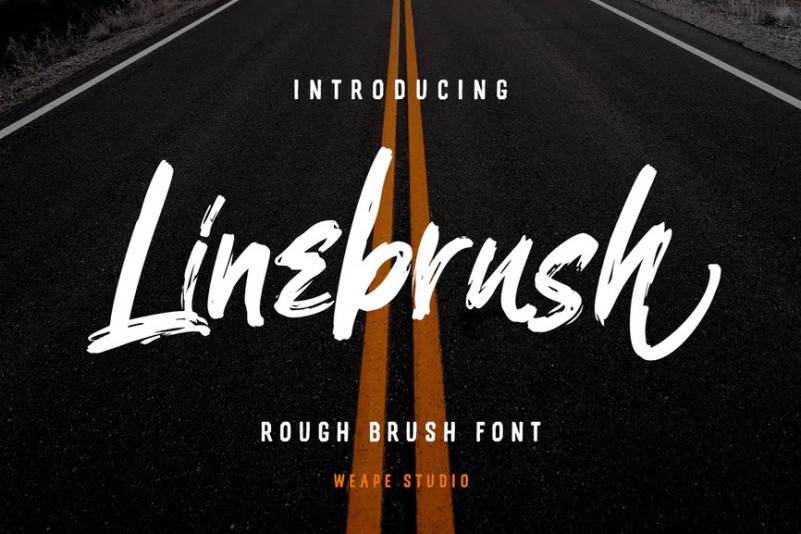
Linebrush Font
Présentation Linebrush – Rough Brush Font, avec des coups de pinceau secs naturels, et le coup de main rapidement. Vous pouvez utiliser et profiter de Linebrush, pour le matériel promotionnel et n’importe quoi pour votre projet.
Et cette police est parfaite pour signature, citations manuscrites, mariage, emballage de produits, mode, photographie, marchandise, projets de marque, affiche, médias sociaux, couverture de livre, cartes de vœux et publicité. Vous pouvez créer plus facilement avec chaque lettre et le faire comme si vous l’aviez écrit vous-même.